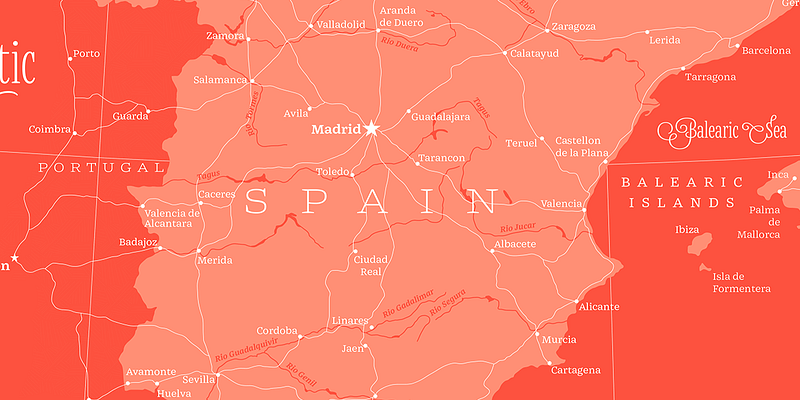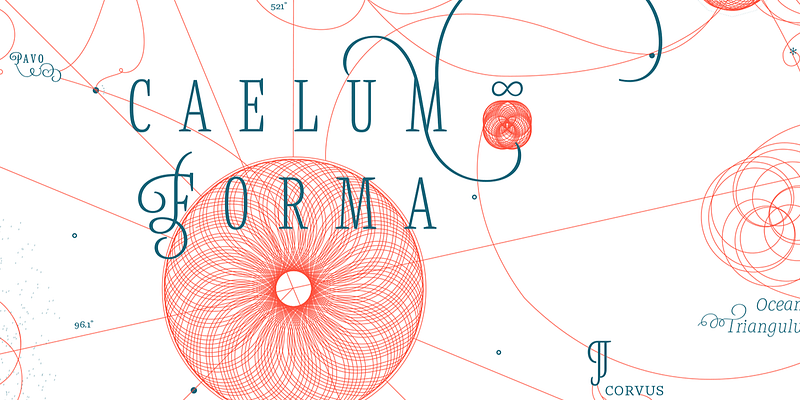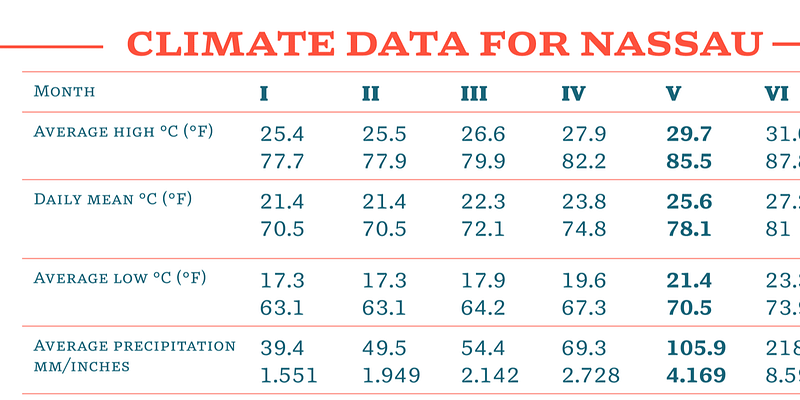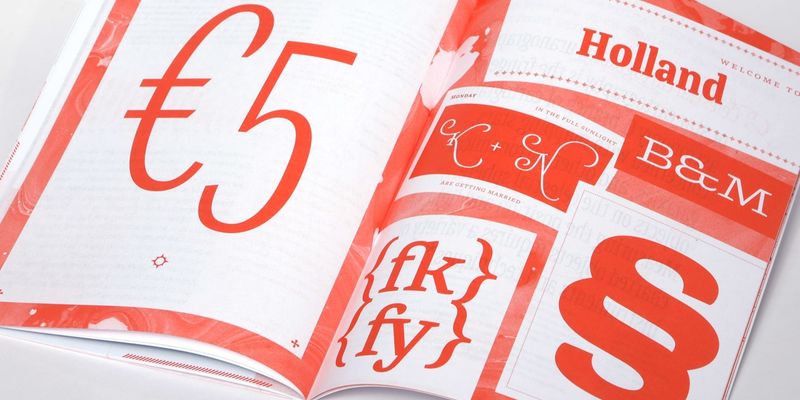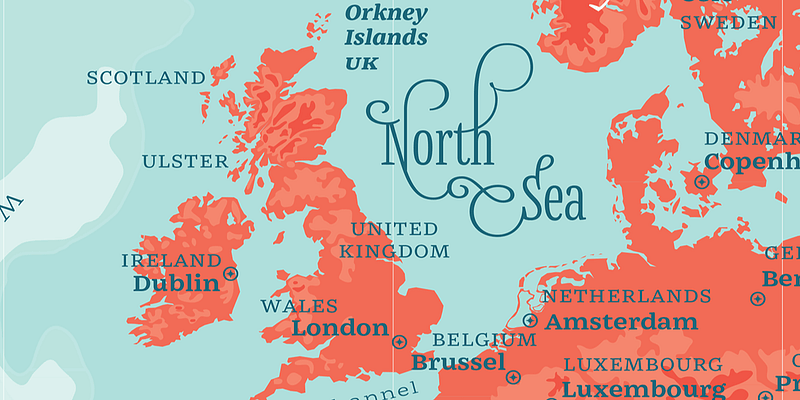
Parcourez le monde avec Mala de Barbara Bigosińska. Inspirés par les polices utilisées sur les cartes et les graphiques, ses 32 styles en trois largeurs sont particulièrement adaptés à l’organisation des informations et à la structuration des textes. Utilisez la largeur normale dans les styles droit et italique pour mettre en forme une grande variété de textes, paragraphes et grands titres compris. La version en caractères étroits permet d’insérer plus de mots lorsque l’espace est restreint, tandis que les proportions généreuses de la version en caractères larges marquent le regard. Le contraste réduit de Mala lui donne une apparence contemporaine et légèrement pittoresque qui rappelle les caractères des machines à écrire. En référence à leur source d’inspiration, tous les styles Mala offrent des capitales décoratives larges avec deux niveaux de complexité pour une typographie exubérante. Bold Monday, 2016.